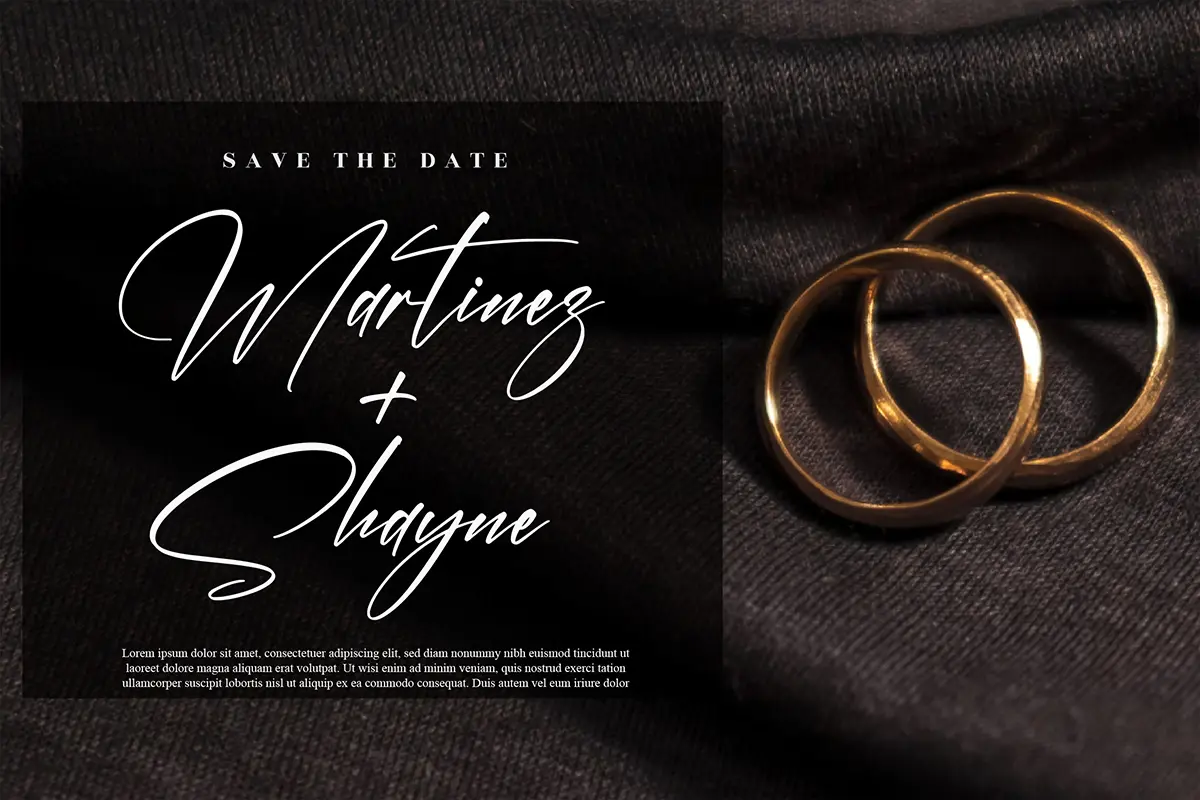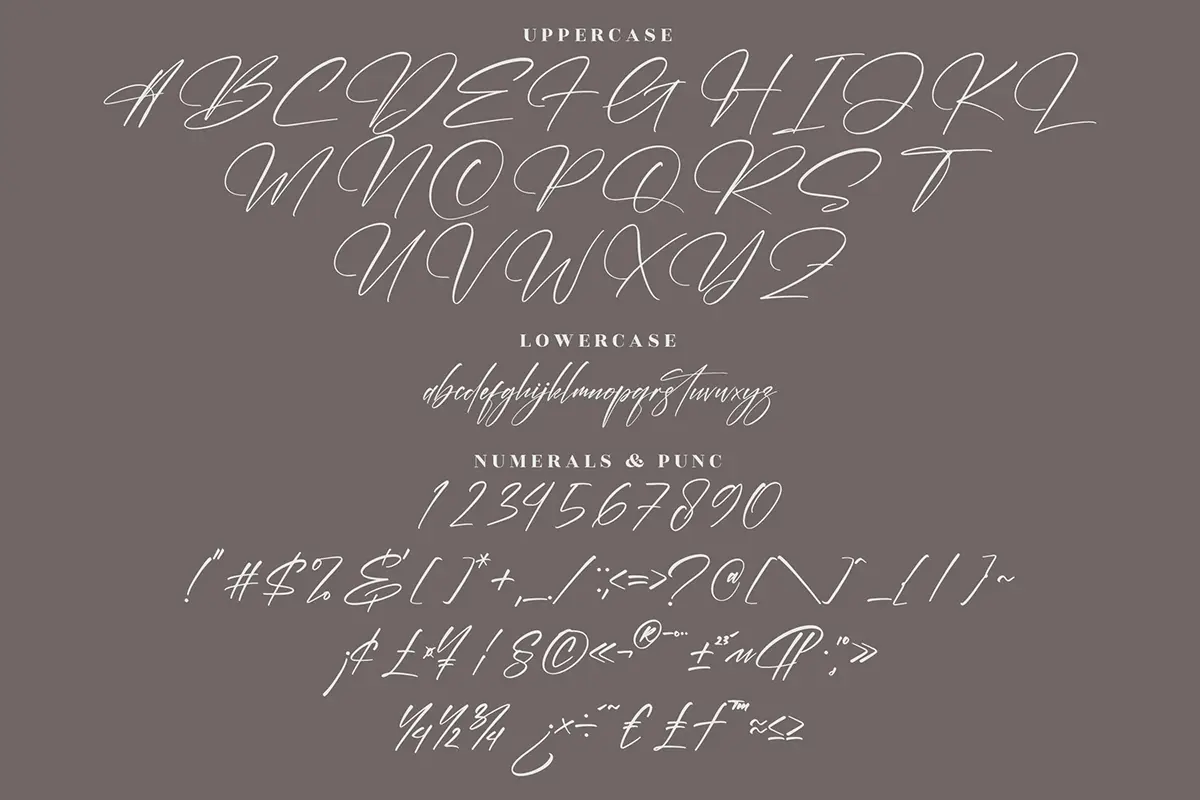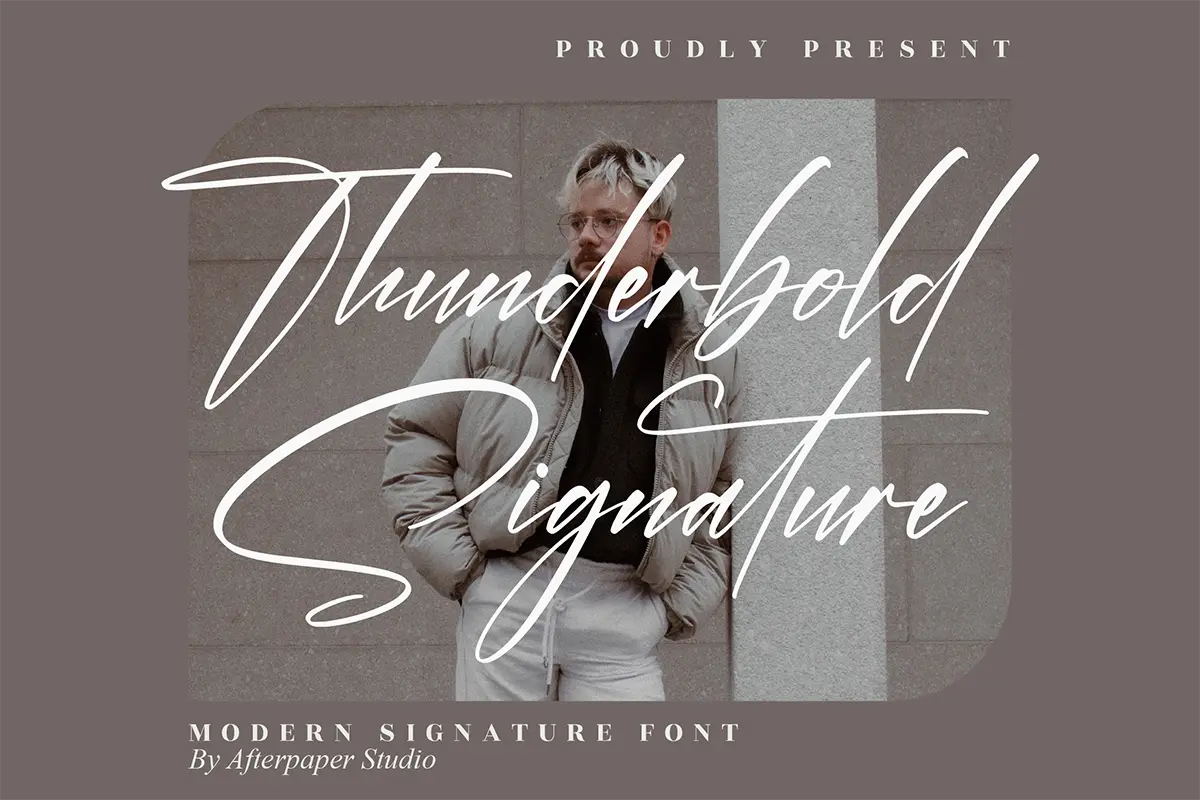
فونت دستنویس امضایی
Thunderbold فونتی دستنویس، ظریف و درعینحال جذاب است که ترکیبی از وقار و لطافت را در طراحیهای شما ایجاد میکند. این فونت برای پروژههایی که نیاز به حس شخصی، هنری و امضامحور دارند انتخابی فوقالعاده است. ظاهر روان و امضایی آن باعث میشود روی دعوتنامههای عروسی، کارتهای تشکر، نقلقولها، کارت تبریک، لوگو، کارت ویزیت و هر طراحی دیگری که به لمس دستنویس نیاز دارد بدرخشد.
⭐ ویژگیهای فونت
- سبک Signature Script با حس طبیعی و دستنویس
- ظاهری شیک، جذاب و متعادل
- مناسب برای طراحیهای لوکس و رمانتیک
- ایدهآل برای لوگو، کارت دعوت، کارت ویزیت و تایپوگرافیهای هنری
- خوانایی بالا در کنار زیبایی بصری
🎯 موارد استفاده
- طراحی دعوتنامه عروسی و مراسمها
- ساخت لوگوهای امضایی و برندهای شخصی
- طراحی کارتهای تشکر و تبریک
- تایپوگرافی نقلقولها و پوسترهای هنری
- استفاده در بستهبندیهای ظریف و محصولات لوکس